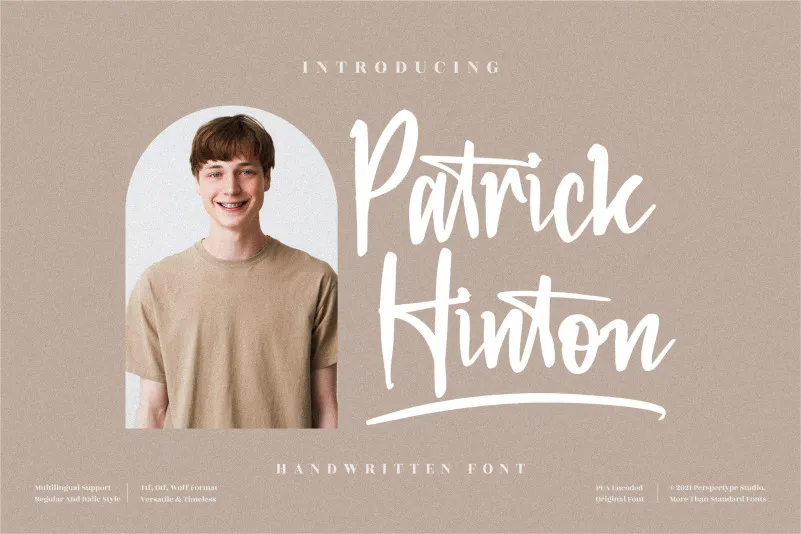
Patrick Hinton Font – Download Grátis
A ‘Patrick Hinton Font’ é uma excelente escolha para designers buscando adicionar personalidade a seus projetos sem perder modernidade ou elegância. Este script font apresenta influências clássicas da caligrafia, mas também traz um toque fresco e atual que o torna perfeito para uso em variados contextos design. É ideal para criar texturas suaves, logotipos distintivos ou até mesmo layouts de página inteira, garantindo uma interação visual atraente e sofisticada. Com sua simplicidade elegante e fidelidade aos traços manuais do script, ela é um recurso indispensável para quem procura equilíbrio entre modernidade e estilo. Esta font oferece uma maneira de incorporar elementos pessoais em seus projetos digitais enquanto mantém a essência das letras escritas à mão, resultando num design único e perfeitamente adaptado ao mundo da tipografia contemporânea.